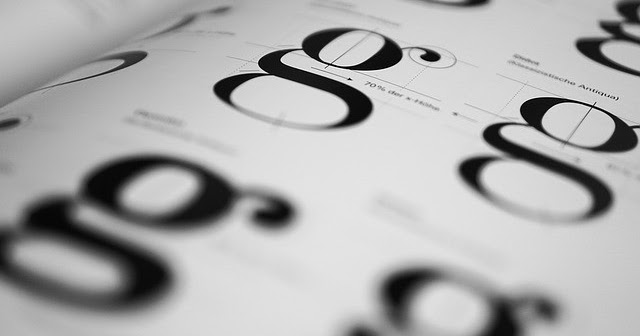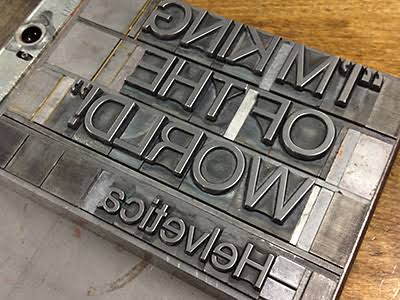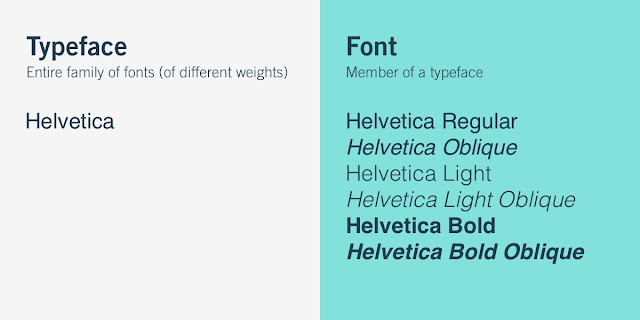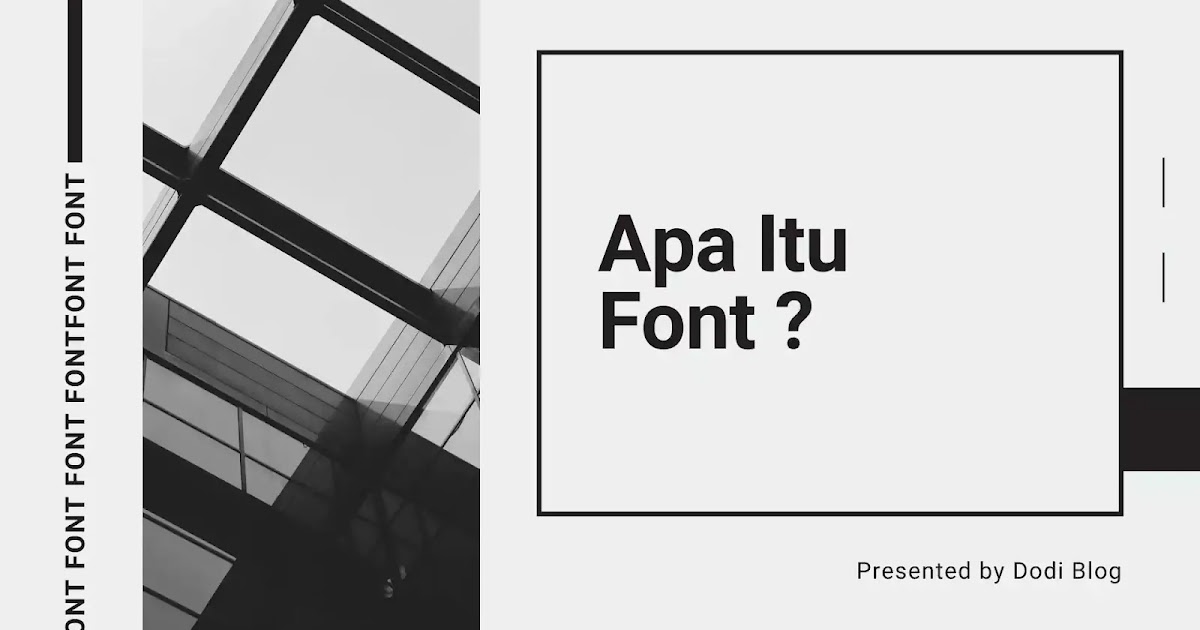
Free Typeface Adalah Istilah Yang Digunakan Untuk Free Typography Fonts
typeface adalah istilah yang digunakan untuk
Typeface adalah istilah yang digunakan untuk. Dalam tipografi ada istilah typeface dan fonttypeface adalah rancangan karakter dari sekumpulan huruf. Ini berhubungan dengan mata kita. Digunakan untuk satu elemen penting dalam desain grafis. Ternyata organ ini sensitif dengan cahaya merah hijau dan biru.
Jenis font display juga dikenal sebagai font untuk judul yang dimaksudkan untuk menarik perhatian pembaca. Bahasa inggris adalah bahasa universal yang mana lazim digunakan di negara mana pun termasuk indonesia. Modern adalah istilah yang digunakan untuk mengkategorikan font dibuat pada saat itu atau dalam gaya saat itu. Beberapa font sans serif yang populer adalah helvetica avant garde dan genewa.